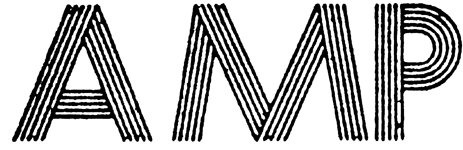
Font gesucht / Lettern aus mehrere Konturen
vielleicht hat jemand einen Tipp für mich. Ich suche einen Font (Grotesk) der wie diese Abbildung, Lettern aus mehreren Konturen besitzt. Meine Suche blieb bisher leider erfolglos.
Nicht genau jene, aber auch mit 5 Linien:
"multi-line" wäre ein geeigneter Suchbegriff.